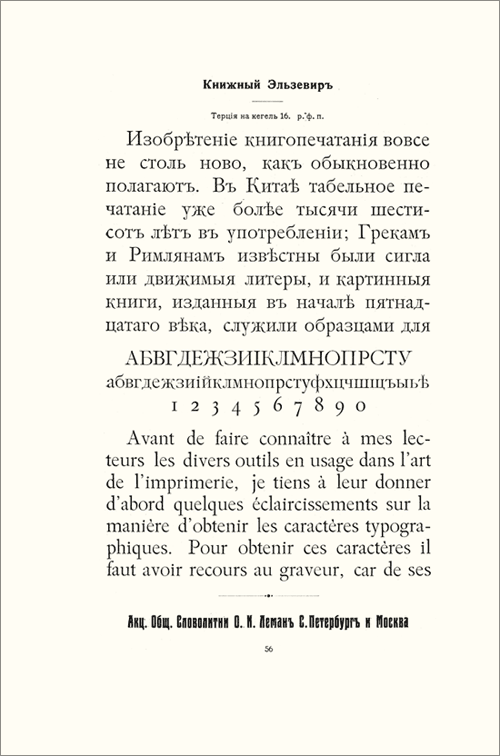
Шрифт Книжный эльзевир/DXElsevierBook
Гарнитура: DXElsevierBook
Тип: Антиква
Начертание: Regular, Italic
"Шрифт Книжный эльзевир появился в словолитне Лемана в конце восьмидесятых годов и широко применялся в изданиях художественной литературы девяностых годов XIX века. Из них следует выделить выпущенные в 1891 году типографией Кушнерова сочинения Лермонтова с рисунками крупнейших художников (Врубеля, Айвазовского, Аполлинария и Виктора Васнецовых, Репина, В.Серова и других), а также издание Звенигородского "Византийские эмали" (1898) и другие.
Текстовый шрифт этого рисунка под названием "медиаваль", а в крупных размерах - "антик" - заслуженно пользовался успехом в одной из лучших типографий Петербурга - Экспедиции заготовления государственных бумаг. Примером удачного использования этого шрифта (во внутреннем и внешнем оформлении книги) служит одно из роскошно оформленных изданий конца XIX - начала XX века "Великокняжеская и царская охота на Руси", вышедшее в 4-х томах в типографии Экспедиции (1896-1911) (В оформлении этого издания принимали участие А.Бенуа, Н. Самокиш, И.Репин, Е.Лансере, В.Суриков, В.Васнецов и другие)
Книжный эльзевир по начертанию и асимметричному решению утолщений в круглых частях букв в некоторой мере сходен с классическими образцами XVII века. Отличается он от них более тонкими штрихами и засечками. Такая модификация в книжном эльзевире была, очевидно, навеяна обыкновенными шрифтами, в то время весьма распространенными. Выделяются в этом шрифте буква «к» и производная от нее «ж», у которых нижнее правое окончание «хвостов» удлиняется за линию строки. Из шрифтов этого периода книжный эльзевир можно считать лучшим. " (Русский типографский шрифт. А.Г.Шицгал, 1974)
Цифровая версия шрифта создана в 2015 году, на основе оттисков из каталога Словолитни О.И.Лемана за 1914 год и Каталога ручных и машинных шрифтов, Издательство Книга, 1969 г.
Гарнитура доработана в 2016 году. Изменен рисунок некоторых знаков, добавлен дополнительный набор цифр, скорректирован межбуквенный интервал.